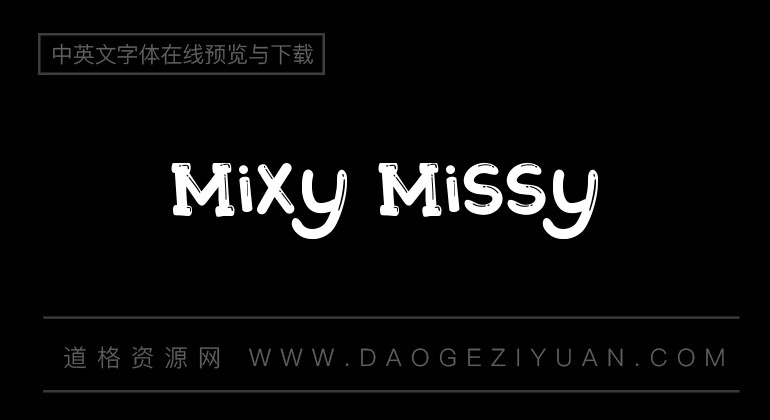
Mixy Missy
? Mixy Missy 是一款可爱的脚本字体,由英国设计师Mandy Millington设计。它采用了英国传统的笔画,以及更多的灵活性,给用户更多的设计选择。它的字体有着温暖的感觉,可以用来创作浪漫的文字设计,也可以用来创作更多的活泼的设计作品。Mixy Missy字体可以用于宣传单页,海报,书籍封面,T恤,招贴等。
Mixy Missy是一款非常不错的手写艺术字体,具有很好的视觉感,适合于文化类的宣传设计、商业类品牌的广告和产品包装设计以及个性化文字排版等较多场景。
Mixy Missy字符映射图